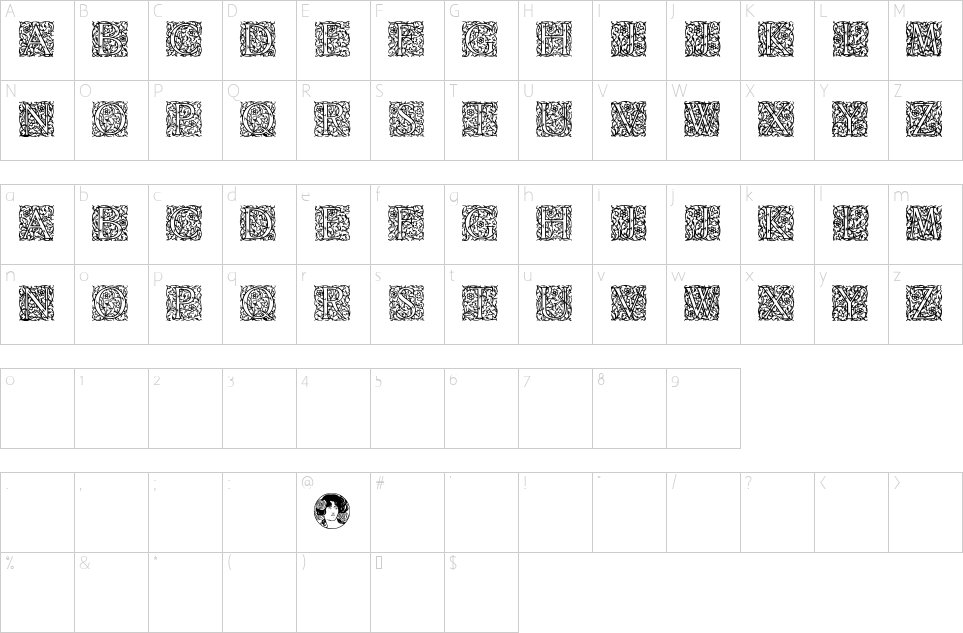
A fonte ‘Arabesque Initialen Font’ é uma elegante escolha para qualquer projeto que busque arquitetura e elegância. Desenhada por Dieter Steffmann, ela carrega um toque de arte rústica e sofisticação, perfeita para gráficos digitais, design de sites, ou qualquer outro uso que exige um toque de sofisticação. Este é um tipo de fonte que adiciona um toque de personalidade ao seu design, seja para gráficos, ilustrações ou design editorial. Descubra por si mesmo o encanto desta fonte e aproveite os downloads gratuitos disponíveis para Windows e Mac. Desde a primeira impressão, você será capaz de criar designs arquitetônicos com uma sofisticação única.